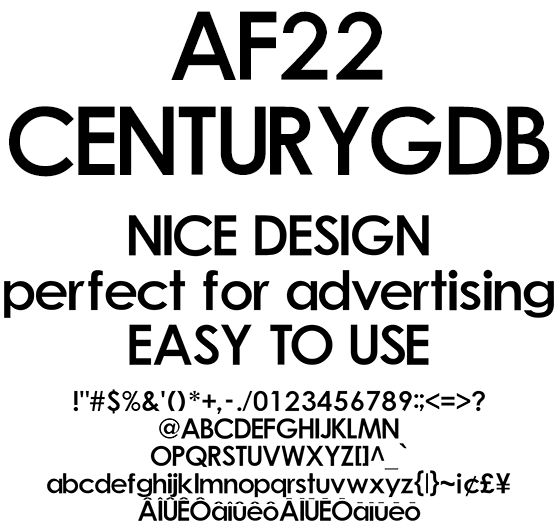
オールマイティな欧文 AF22CENTURYGDB
AF22CENTURYGDB
見慣れたデザインで読みやすいデミボールドゴシック体、リーフレットやお洒落なドキュメントに最適。個人同人向けアニメ、動画向けなフォント。記号類、マクロンやサーカムフレックスなどのダイアクリティカルマーク追加。日本のローマ字表記で使われる訓令式やヘボン式で扱う Ô や Ō を収録、人名地名でもお使い頂けます。